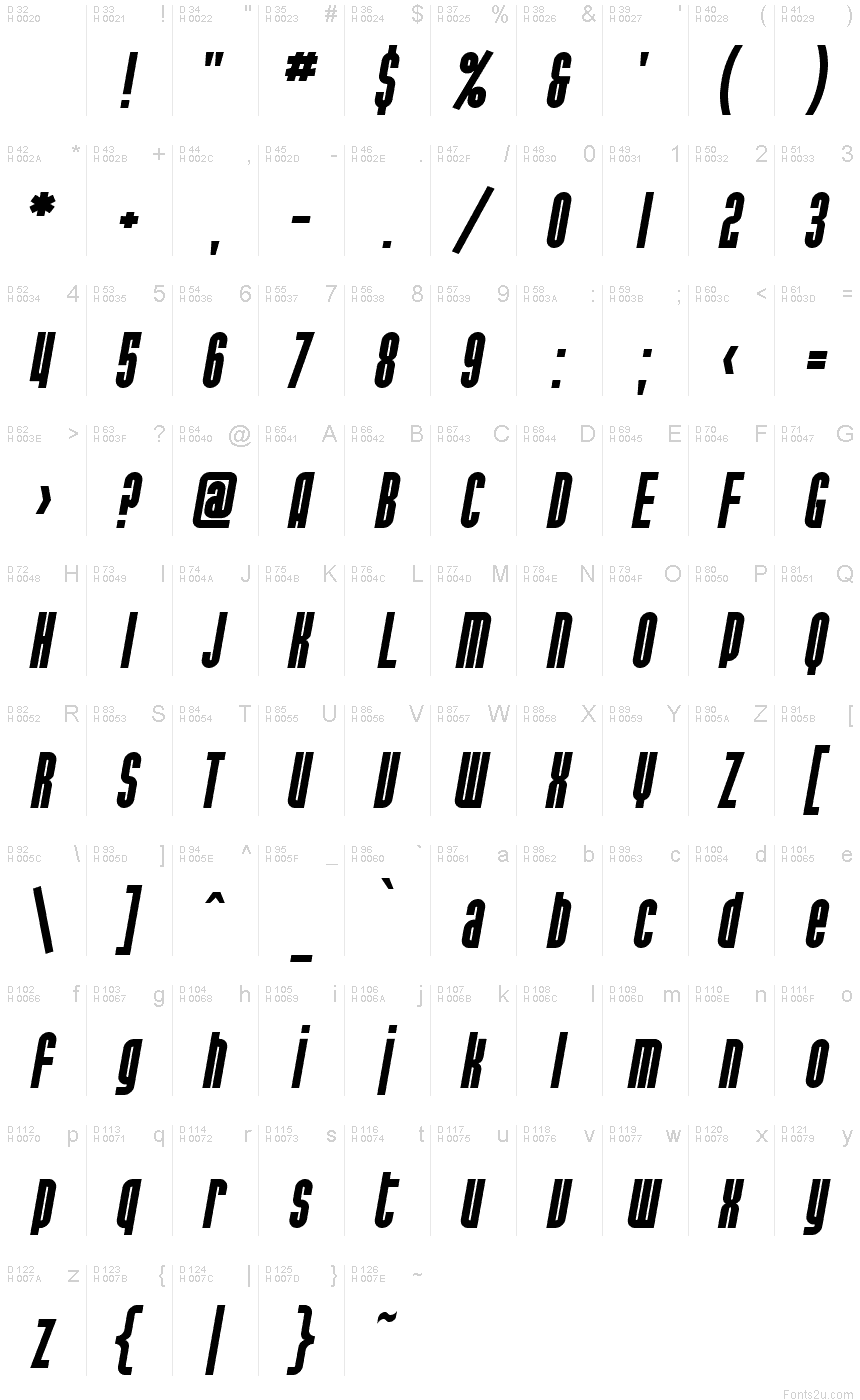
SF Port McKenzie Bold Italic
SF Port McKenzie Bold Italic od ShyFoundry to darmowy, kondensowany krój bezszeryfowy w kursywie, o wyrazistym, niemal plakatowym charakterze. Litery pochylają się do przodu w gęstym rytmie, łącząc ciężkie kreski z ciasnym kerningiem oraz ostrymi, kanciastymi cięciami, co nadaje całości szybkiego, miejskiego tempa.
Świetnie sprawdzi się na ulotkach muzycznych, w identyfikacji wizualnej sportu, na plakatach eventowych, okładkach magazynów i planszach tytułowych, wszędzie tam, gdzie darmowy font musi mieć siłę przebicia, nie stając się przy tym prostym gadżetem. Ze względu na wąskie, zdecydowane formy, pasuje też do krótkich nagłówków i układów tekstowych, które mają sprawiać wrażenie pilnych, zwartych i lekko surowych.